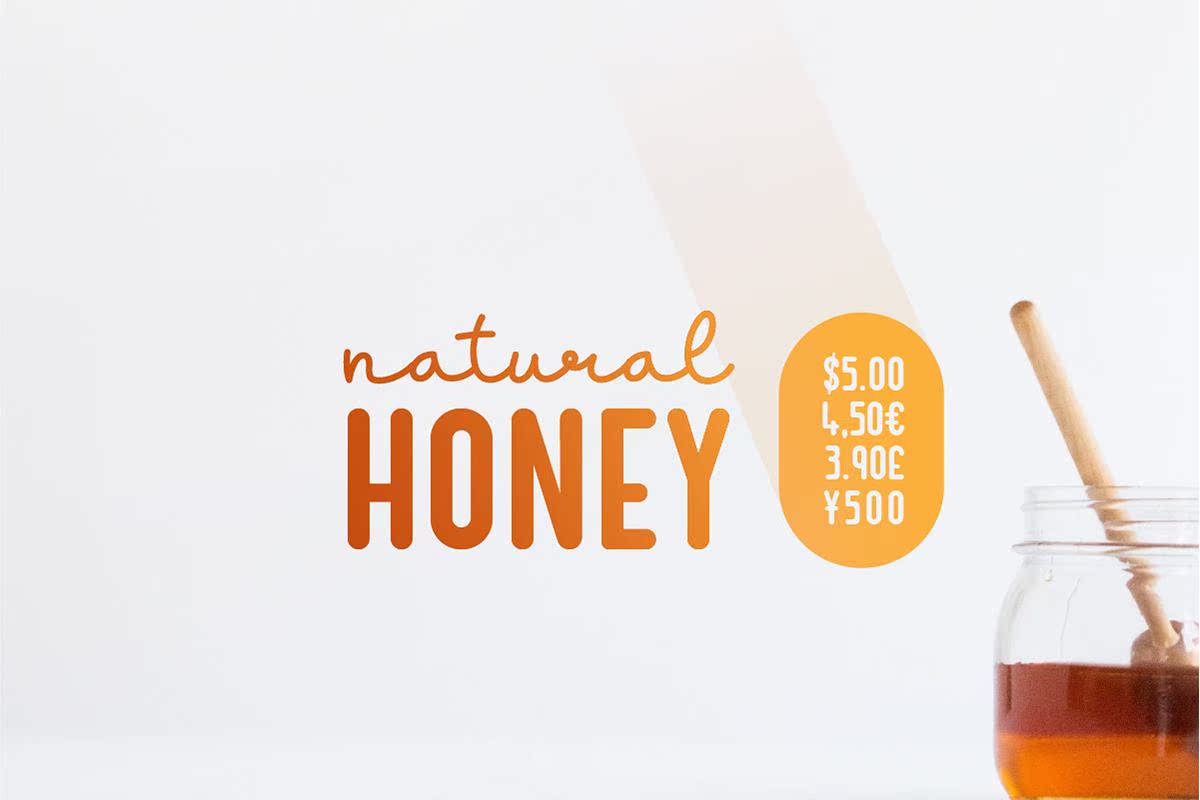
简介Gargio Free TransseryFunt。它可以与可选模板一起使用。这也是适用于头条新闻或徽标的几何图形和特征字体。不要忘记将可选模板设置为YeCatcher,从而使您的工作不受此限制,只需输入“theliga”,您将获得一个独立的预先设计的Eyecatcher。还有更多的连字!但是,此免费信息来源于PersonalUse许可证,使您可以购买RefFeatures。